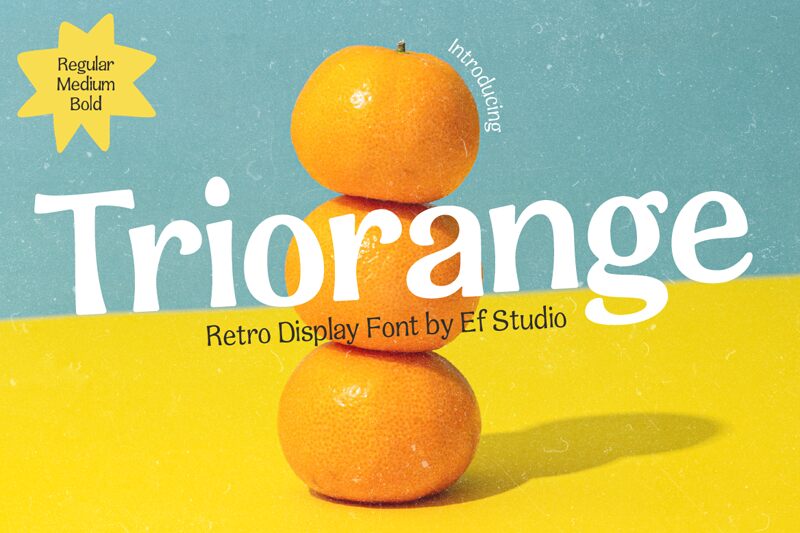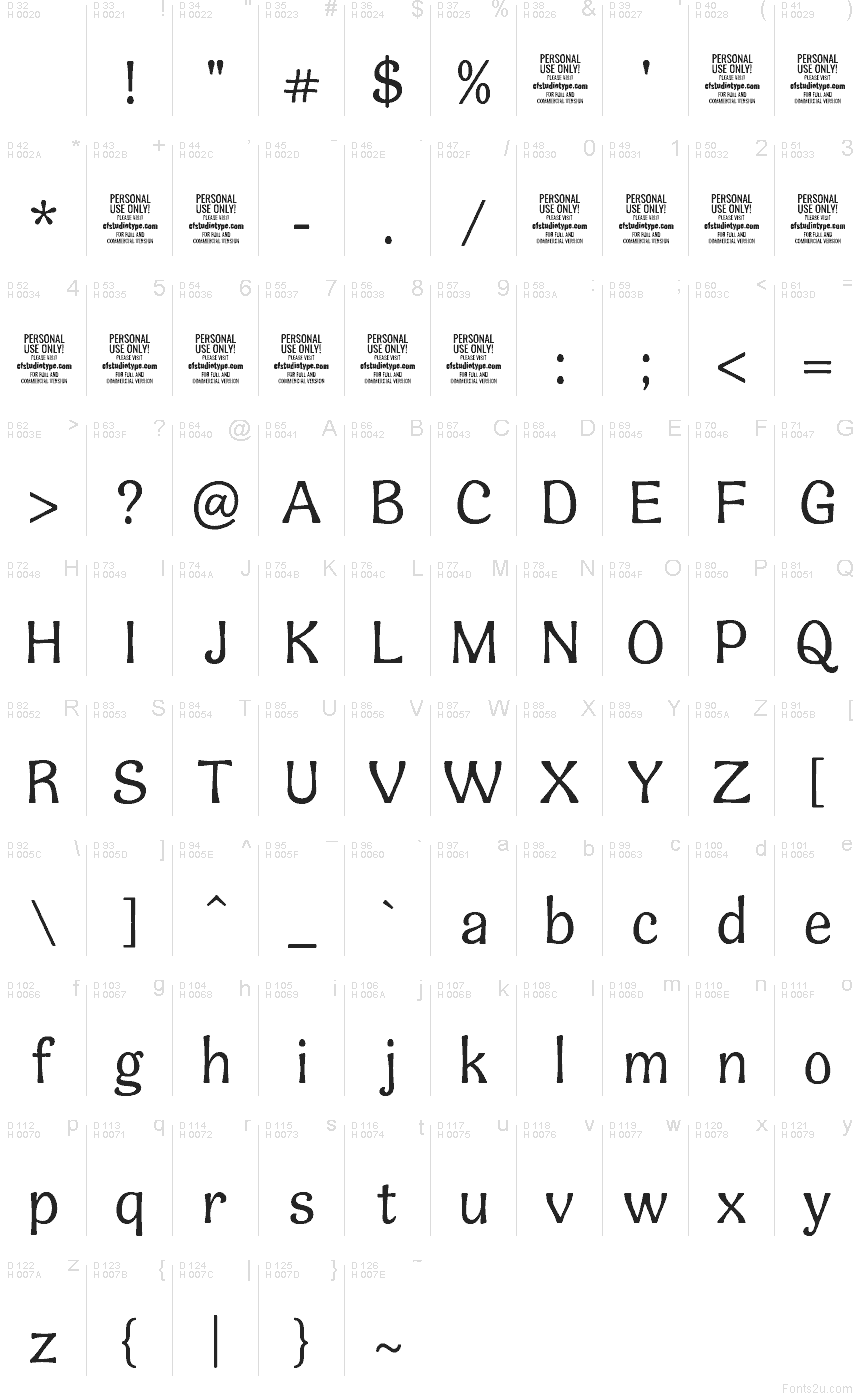
Triorange par EF Studio est une police d'affichage rétro gratuite aux courbes douces dessinées à la main et aux traits calligraphiques légèrement irréguliers. Ses caractères mélangent des formes arrondies avec quelques crochets plus nets, conférant à l'ensemble un rythme vintage décontracté, sans jamais paraître surchargé.
Triorange est idéale pour les titres d'affiches, les logos, le packaging, les menus de café, les visuels de réseaux sociaux et les courtes citations éditoriales. Sa structure dessinée et légèrement informelle apporte une touche personnelle à vos créations tout en conservant une mise en page équilibrée et facile à intégrer.